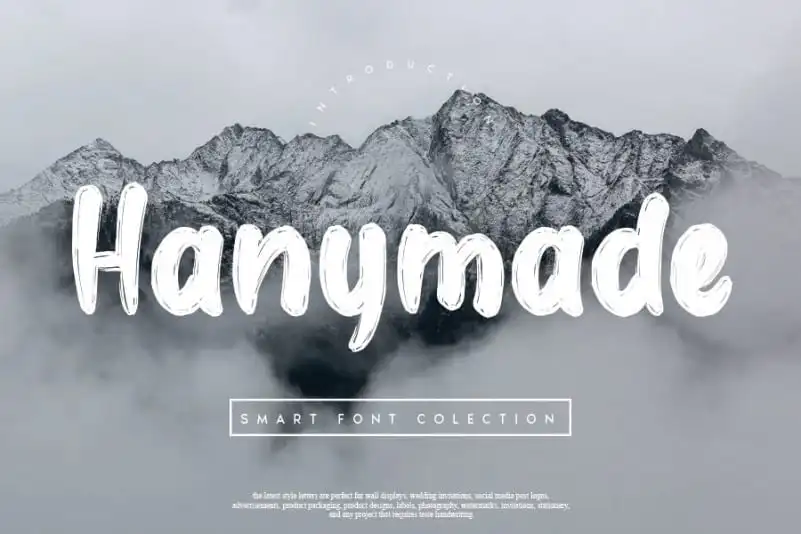
Hanymade Script Font – Download Grátis
A Hanymade Script Font é uma deliciosa e amigável fonte feita à mão. Ela tem um estilo natural e único que torna-a perfeita para diversos designs. A única restrição é a sua imaginação. Esta fonte, com sua delicada escrita de pessoa ao lado, seria um excelente complemento em qualquer projeto gráfico. Seja você quem criou algo inovador ou simplesmente busca uma fonte que adiciona um toque pessoal aos seus designs, Hanymade Script Font certamente se encaixa perfeitamente. Através da elegância e personalidade desta fonte, você pode explorar novas ideias em sua próxima criação visual.